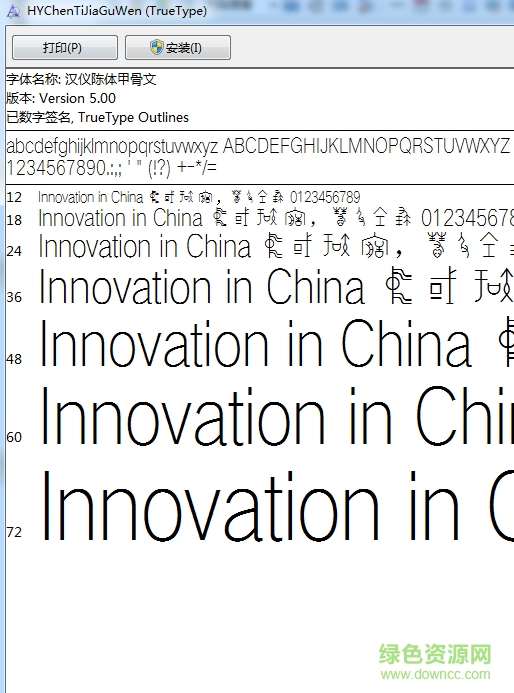
漢儀陳體甲骨文作為全球首款甲骨文字庫(kù),由漢儀字庫(kù)合作設(shè)計(jì)師陳楠設(shè)計(jì),為廣大喜歡字體的朋友提供不錯(cuò)的學(xué)習(xí)平臺(tái),綠色資源網(wǎng)為您提供下載!
漢儀陳體甲骨文
全球第一套甲骨文設(shè)計(jì)字庫(kù),
穿越千年,以最炫酷的方式潮熱來(lái)襲!
嘻哈穿越千年,為甲骨文打CALL!
漢儀陳體甲骨文非常有特點(diǎn),融合嘻哈風(fēng)格,創(chuàng)意十足,絕對(duì)讓書(shū)法家大開(kāi)眼界的甲骨文字體,歡迎下載使用!